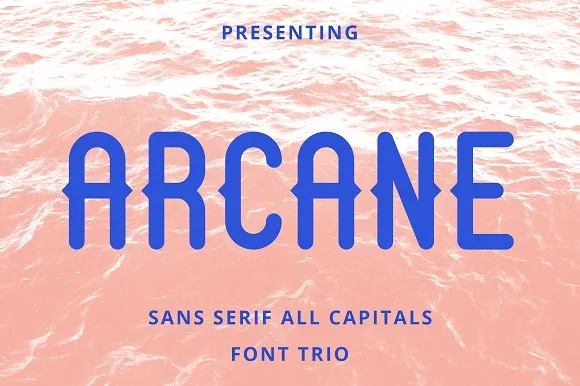
Arcane Sans Font Trio – Download Grátis
Introduzimos a Arcane Font, criada pelo designer Seceme Shop. Esta é uma fonte premium disponível para download na Creativemarket, mas está agora gratuita hoje. Arcane é um tipo de sans-serif vintage com um toque moderno. É perfeito para headings, designs retro, logos vintage, design de embalagens e impressões. Para resultados ótimos, recomendamos combinar a Arcane com outro tipo de sans-serif em maiúsculas. Para quem está buscando uma fonte que combine elementos de antiguidade com um toque contemporâneo, a Arcane é a escolha perfeita. Sua simplicidade e elegância tornam-a versátil o suficiente para diferentes aplicações, sem perder seu charme nostálgico. Esta font pode deixar seu design mais dinâmico e moderno ao mesmo tempo que mantém uma conexão com o passado.